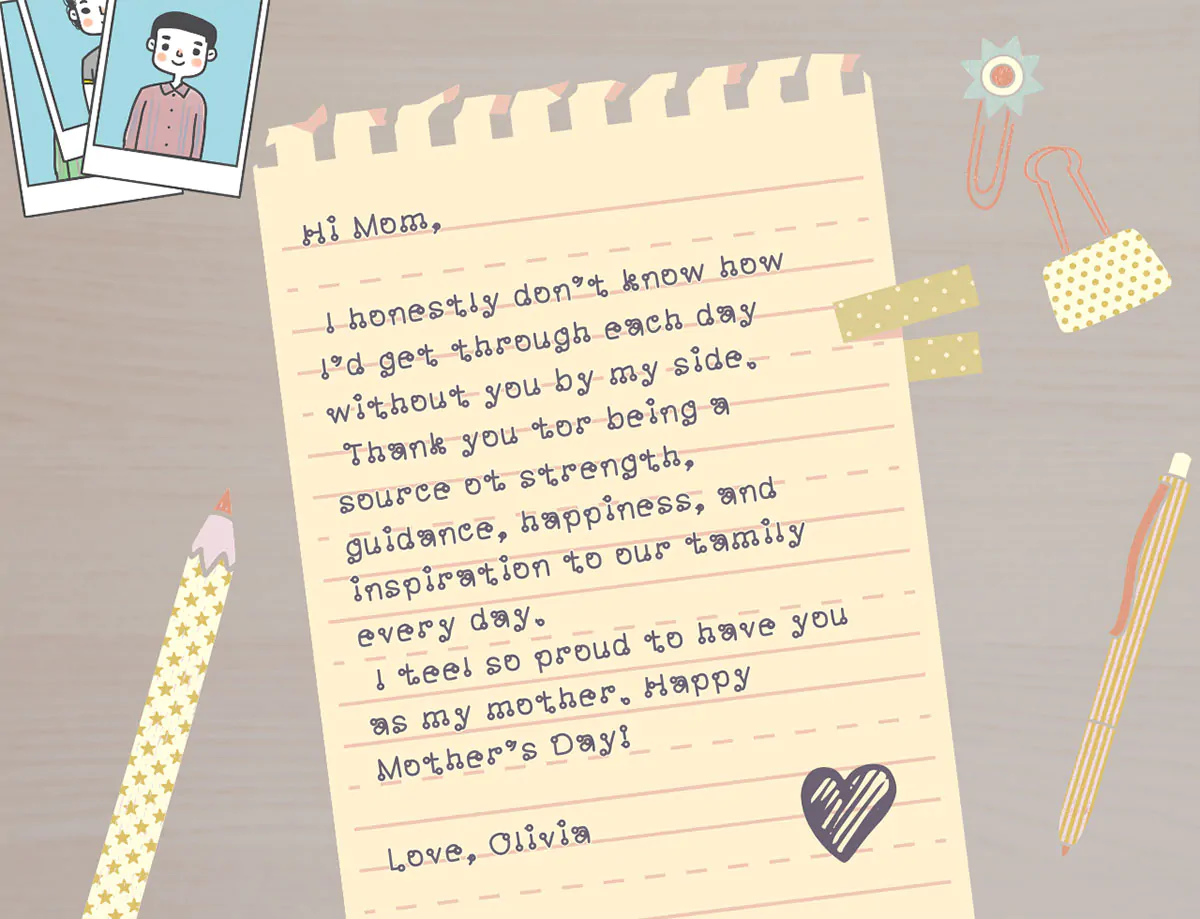
فونت فانتزی Middle
فونت فانتزی
فونت فانتزی Middle یک قلم دستنویس و زیبای انگلیسی است که مناسب برای استفاده در طرح و پروژههای کودکانه میباشد.
برای تایپوگرافی، پوستر، هویت بصری و محتوای چاپی یا دیجیتال قابل استفاده است.